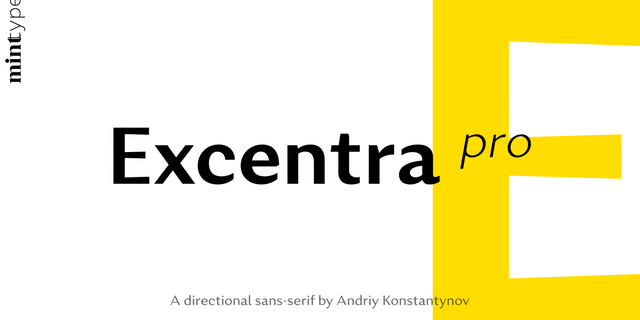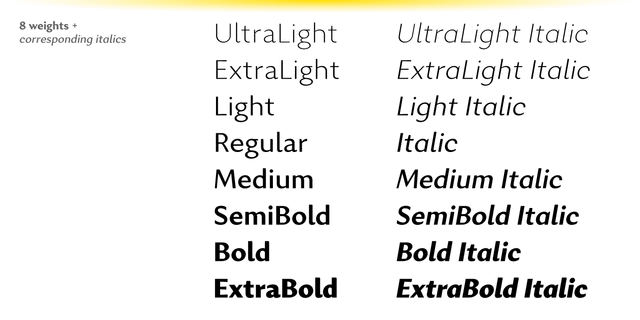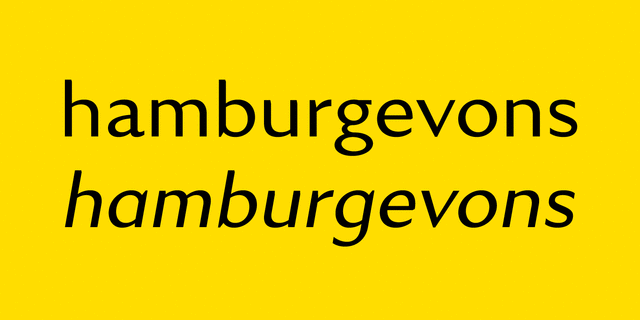
Excentra Pro – гротеск, вдохновленный шрифтовыми работами из 1920-х и дополненный гуманистической вариацией толщины штриха с наклонной осью. Специфический элегантный рисунок делает Excentra Pro подходящей для использования в журналах, брендинге, а также для набора крупных массивов текста. Гарнитура содержит 8 весов + курсив с поддержкой множества языков. Поддержка OpenType включает лигатуры, капитель, 6 наборов цифр, верхние и нижние индексы, дроби, верхние буквенные индексы для латинских строчных, специализированный набор пунктуации для набора заглавными и языковые альтернативы. Также включена поддержка заглавной немецкой Эсцет.
Шрифт Excentra Pro разработал и выпустил Андрей Константинов в студии Mint Type в 2017 году.
чистый, прохладный, свежий, эффектный, модный, качественный, культурный, отборный, благородный, гармоничный, элитный, дорогой, роскошный, красивый, мастерский, эстетичный, художественный, знаменитый, оригинальный, комильфо, богатый, современный, городской, яркий, выразительный, пафосный, монументальный, серьезный, авторитетный, надежный, важный, твердый, гордый, четкий, образованный, джентльменский, сексуальный